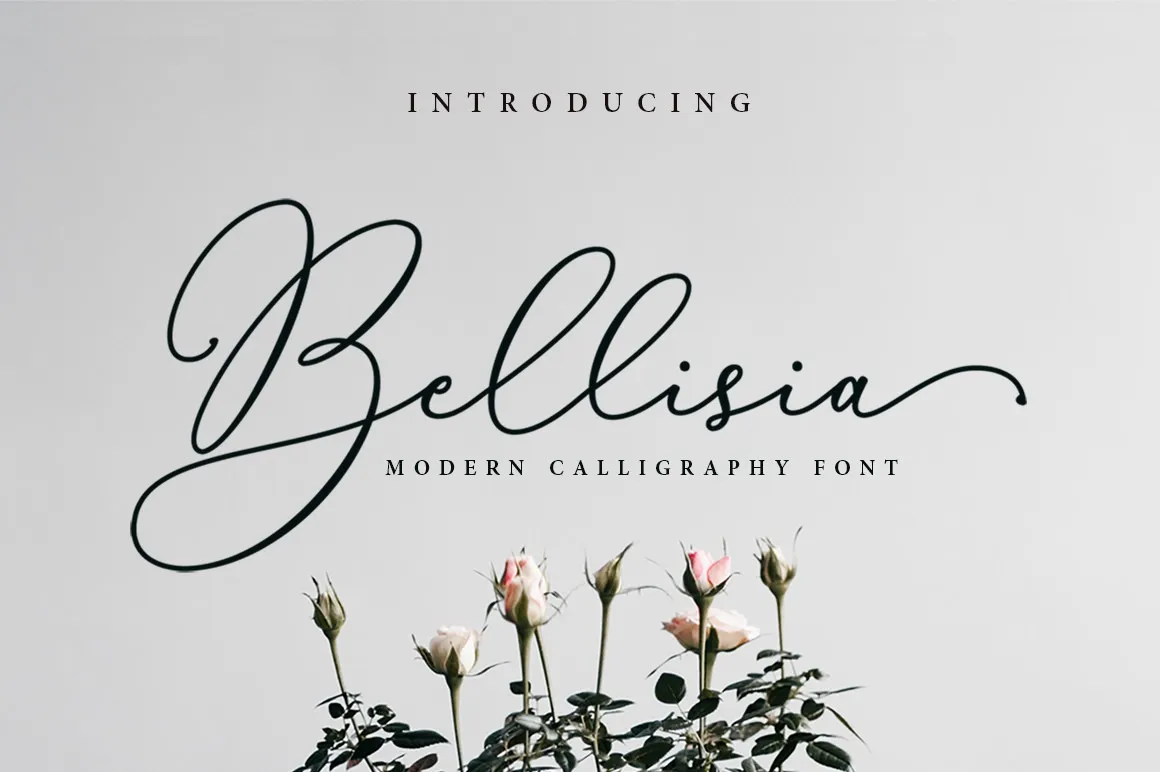
Bellisia Font – Fonte Grátis
Bellisia Font
A Bellisia Font é uma elegante escolha para os criativos que desejam adicionar um toque moderno à suas criações digitais. Desenvolvida pelo site 99designs, esta font é perfeitamente adaptada a projetos variados. Ela se destaca por sua simplicidade e beleza com swashes, tornando-a uma excelente escolha para estilos como logotipos, cartões de cumprimentos, design de embalagens, identidades de marcas, designs artesanais, e qualquer projeto DIY. Com seus traços fluidos e formas levemente românticas, a Bellisia é perfeita para expressar uma personalidade casual. Seu uso em nomes de livros, convites de casamento, embalagens de produtos ou até mesmo em anúncios digitais pode fazer um impacto único e memorável. Essa font é mais que um recurso para designers gráficos; ela é o coração vibrante para qualquer projeto onde deseja transmitir uma mensagem bonita e simples, tornando-a ideal para qualquer aplicação criativa.